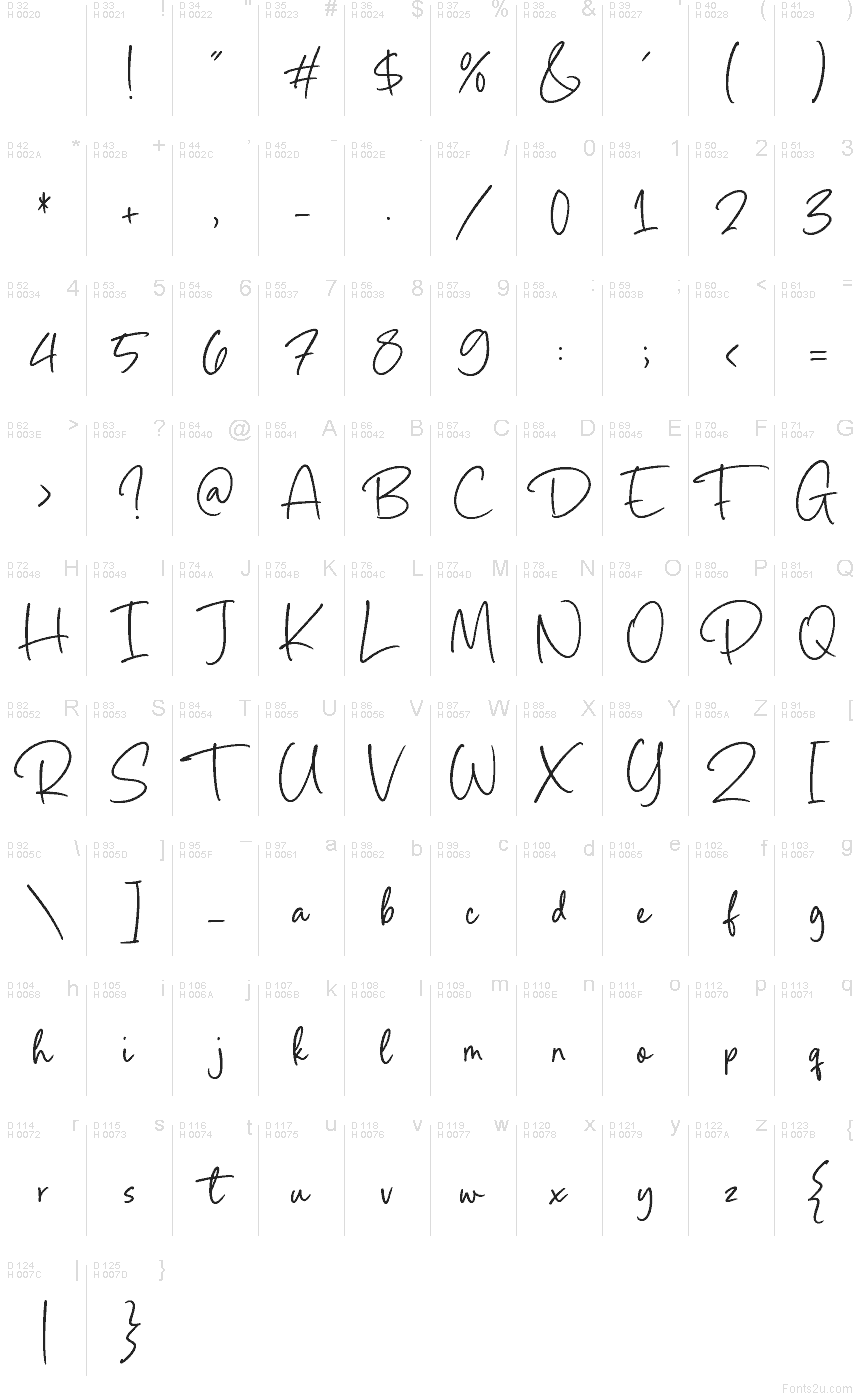
Písmo Palms Delight od studia Timur Type Studio je bezplatný rukou psaný font s volnou, plynulou linkou a dlouhými smyčkami, které dodávají textu uvolněný, osobní rytmus. Tvary zůstávají jednoduché a otevřené, s oblými křivkami a nenucenou vyvážeností, která působí spíše jako rychlá práce perem než jako formální kaligrafie.
Palms Delight je font zdarma, který skvěle funguje pro svatební oznámení, přáníčka, loga, obaly, citáty na sociální sítě a krátké akcenty ve stylu podpisu. Díky svému vzdušnému provedení je přirozenou volbou, když hledáte text, který působí osobně a jemně dekorativně, aniž by byl příliš zdobný.
Palms Delight je rukou psaný font typu script.
Palms Delight také podporuje mnohojazyčnost.